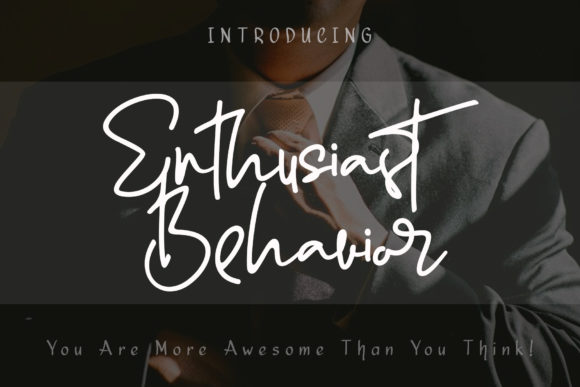
Creativefabrica Enthusiast Behavior Font
[Creativefabrica] Enthusiast Behavior Font
Энтузиастское поведение - это простой, но стильный шрифт.
Он включает в себя начальные и конечные точки, которые идеально подходят для придания стильного и элегантного вида вашим дизайнерским работам.